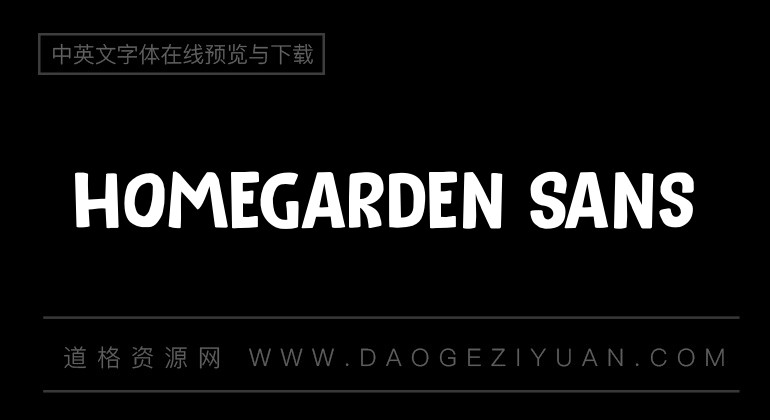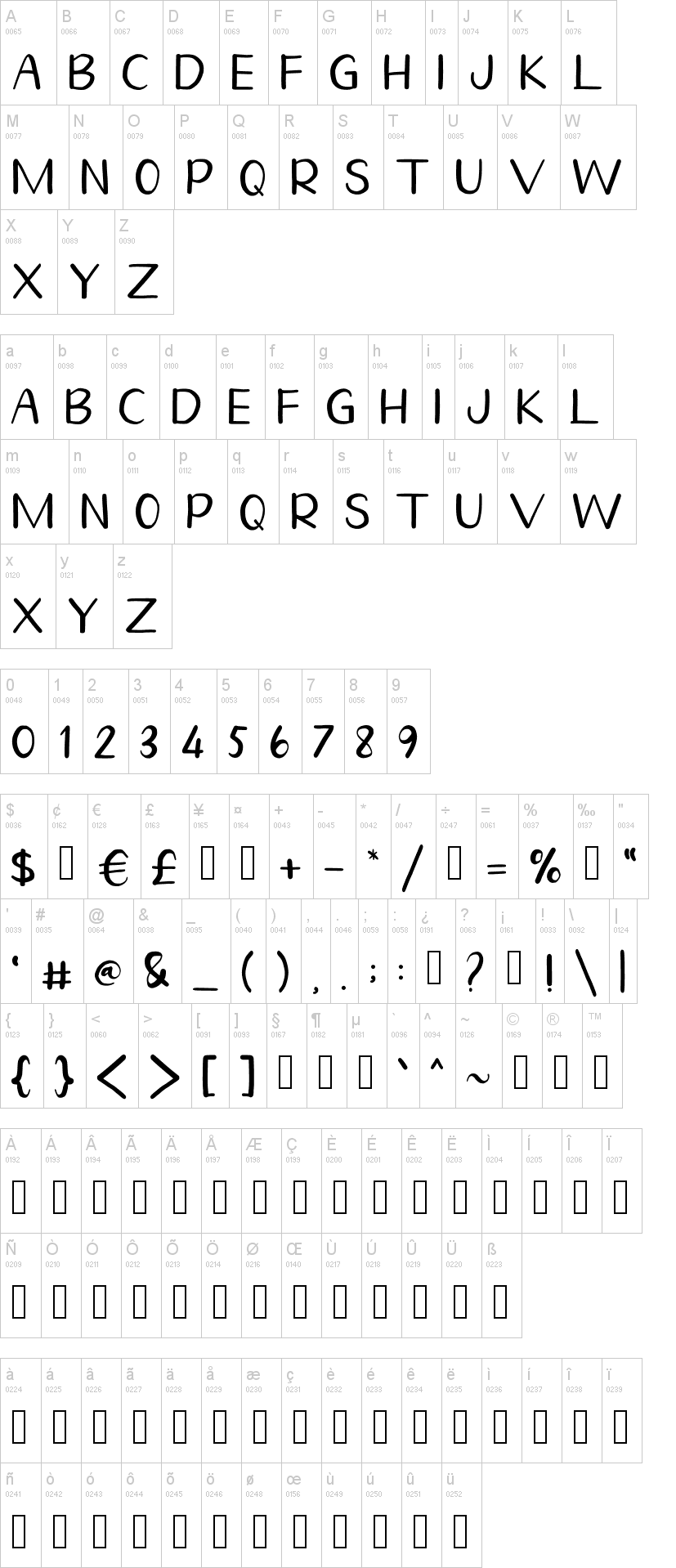
Homegarden Sans 是一种现代风格的无衬线字体,由设计师 Jay White 创建。它的设计灵感来自于自然和花园,这也是它的名称的由来。这种字体具有一种温暖、亲和力和自然的感觉,适合用于印刷物、广告、标志、网站、海报等多种应用场景。 Homegarden Sans 字体有多种字重和样式可供选择,包括 Light、Regular、Medium、Bold 和 Black 等字重,以及常规、斜体和粗体等样式。此外,它还支持多种字形,如大小写字母、数字、标点符号和特殊字符等。 Homegarden Sans 字体的特点是具有明显的对比度,字母间距宽松,不过度装饰,同时也具有垂直和水平方向的稳定性。它的风格简洁明了,易于阅读,非常适合用于设计温暖、亲和力强的品牌形象。内容介绍
Homegarden Sans是一款非常不错的手写艺术字体,具有很好的视觉感,适合于文化类的宣传设计、商业类品牌的广告和产品包装设计以及个性化文字排版等较多场景。